2023년 최고의 책 글꼴 26개(무료 및 프리미엄)
게시 됨: 2023-08-22프로젝트를 한 단계 더 발전시킬 수 있는 완벽한 글꼴을 찾고 있는 그래픽 디자이너이신가요? 더 이상 보지 마세요! 이 블로그 게시물에서 우리는 책 글꼴의 세계, 특히 2023년 트렌드로 설정된 글꼴에 대해 알아볼 것입니다.
하지만 이 글꼴이 내가 이미 가지고 있는 글꼴과 왜 그렇게 특별하고 다른지 궁금하실 것입니다. 함께 살펴보겠습니다.
이 글에서는 디자인에 새로운 생명을 불어넣어 줄 가장 아름답고 독특한 책 글꼴 27가지를 소개합니다. 이러한 글꼴은 인기도, 다양성, 전체적인 디자인 미적 향상 능력을 바탕으로 세심하게 선별되었습니다.
각 글꼴에는 고유한 개성이 있어 프로젝트에 깊이와 개성을 더해줍니다.
그렇다면 책 글꼴이 모든 그래픽 디자이너에게 꼭 필요한 이유는 무엇일까요? 글쎄요, 통계에 따르면 올바른 글꼴이 메시지 수신 방식에 중요한 영향을 미칠 수 있습니다.
실제로 연구에 따르면 특정 글꼴은 특정 감정과 연관성을 불러일으켜 궁극적으로 독자가 작업을 해석하고 참여하는 방식에 영향을 미칠 수 있습니다.
이를 염두에 두고 디자인 목표에 부합할 뿐만 아니라 대상 고객과 연결되는 글꼴을 선택하는 것이 중요합니다.
이제 북 글꼴의 세계로 바로 뛰어들어 우리가 준비한 놀라운 선택을 살펴보겠습니다.
책 표지, 포스터, 잡지 레이아웃 등 어떤 작업을 하든 이러한 글꼴은 디자인에 우아함과 정교함을 더해줍니다. 영감을 얻고 프로젝트를 새로운 차원으로 끌어올릴 완벽한 글꼴을 찾아보세요.
최고의 프리미엄 북 글꼴
책 디자인을 한 단계 더 발전시키고 싶으십니까? 더 이상 보지 마세요! 이 섹션에서는 프로젝트에 전문성과 우아함을 더해줄 최고의 프리미엄 북 글꼴을 모았습니다. 최고의 글꼴을 확인하고 디자인에 어떤 변화를 가져올 수 있는지 확인해 보세요.
미끄러운
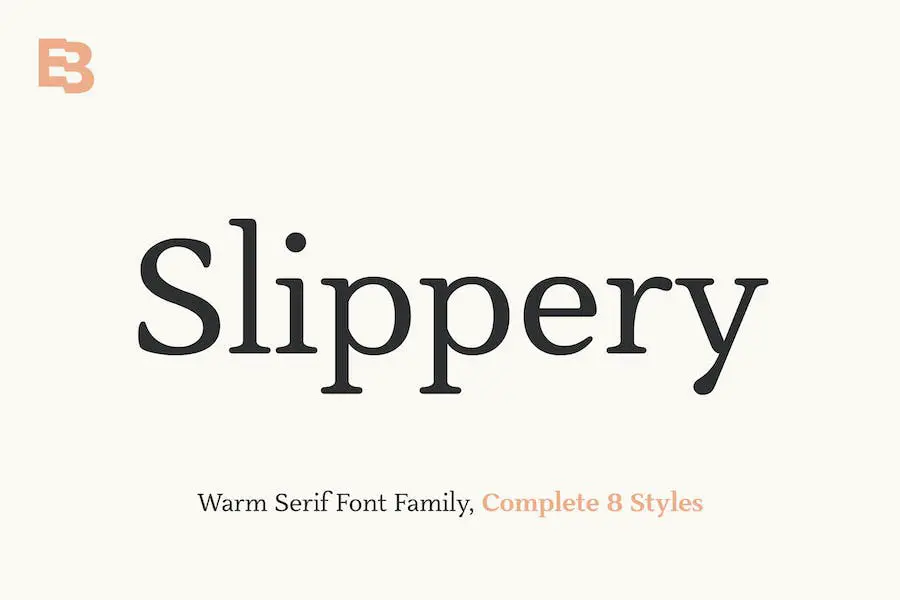
Slippery는 가독성을 높이기 위해 특별히 디자인된 따뜻한 세리프 글꼴입니다. 서체는 부드러운 가장자리, 넓은 카운터, 적당한 x 높이 및 독특하고 우아한 느낌을 주는 아름다운 이탤릭체를 특징으로 합니다.
GT 리카르도
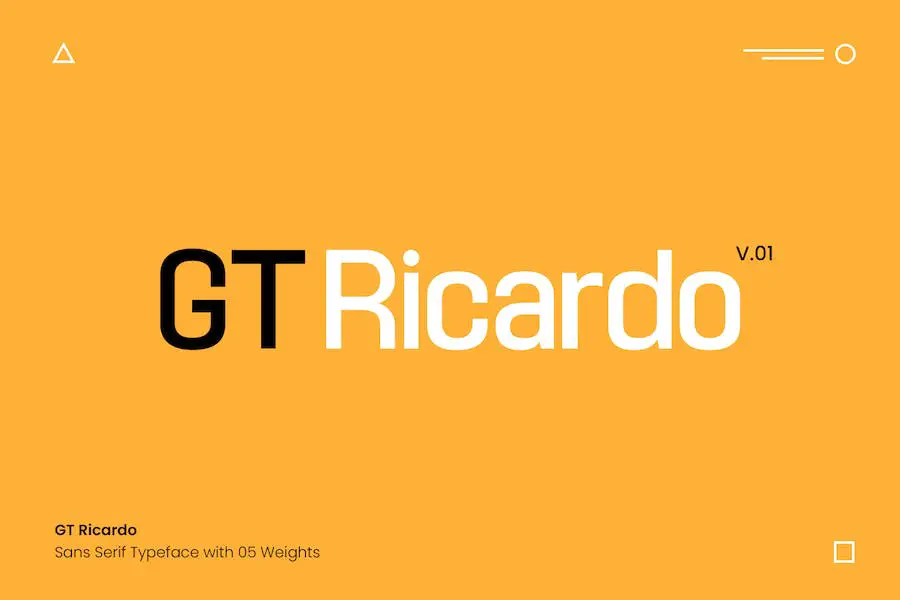
GT Ricardo는 Light, Regular, Medium, SemiBold, Bold 서체의 5가지 두께를 지닌 새롭고 우아한 서체입니다. 200개 이상의 글리프가 포함된 숫자와 확장 구두점을 제공하여 모든 프로젝트에 대한 다양성을 보장합니다.
전문적인 커닝과 품질 높은 장인정신으로 인해 이 서체는 신뢰할 수 있는 선택이 되었습니다. 로고, 잡지, 영화 또는 기타 디자인 프로젝트 작업을 하든 GT Ricardo는 통제된 글자체와 현대적인 터치로 작업의 수준을 높여줄 것입니다.
깨끗하고 미니멀한 스타일은 가독성과 다양성을 유지하면서 따뜻함과 기발함을 발산합니다. 브랜딩부터 헤드라인, 캡션, 문단, 포스터까지 GT Ricardo는 아름다움을 타협하지 않고 지속적인 인상을 남길 수 있도록 디자인되었습니다.
벨리아우
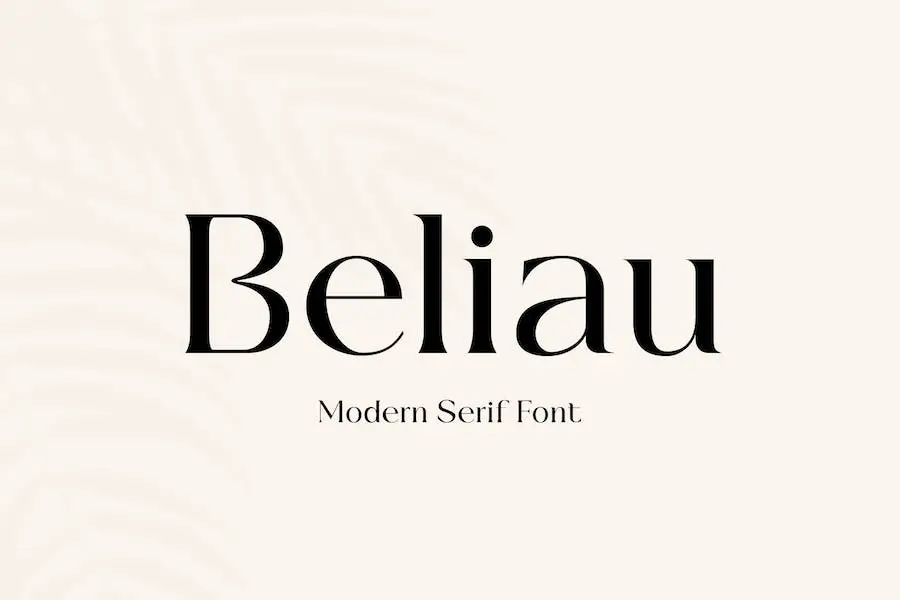
Beliau는 고해상도 디스플레이 및 인쇄 매체용으로 특별히 제작된 놀랍고 현대적인 세리프 글꼴입니다. 우아한 미학과 균형 잡힌 비율 덕분에 헤드라인, 기업 브랜딩 및 세련미가 필요한 기타 디자인 프로젝트에 사용하기에 이상적입니다.
최신 기술을 염두에 두고 설계된 Beliau는 심지어 가장 발전된 화면에서도 모든 캐릭터가 선명하고 명확하도록 보장합니다. 부드러운 선과 정밀한 디테일은 텍스트에 세련미를 더해 시각적으로 매력적이고 읽기 쉽습니다.
웹사이트를 제작하든, 로고를 디자인하든, 인쇄 레이아웃 작업을 하든 Beliau의 다재다능함은 빛을 발합니다. 다양한 디자인 응용 프로그램에 쉽게 적응하여 프로젝트에 전문적이고 세련된 모습을 선사합니다.
메리북
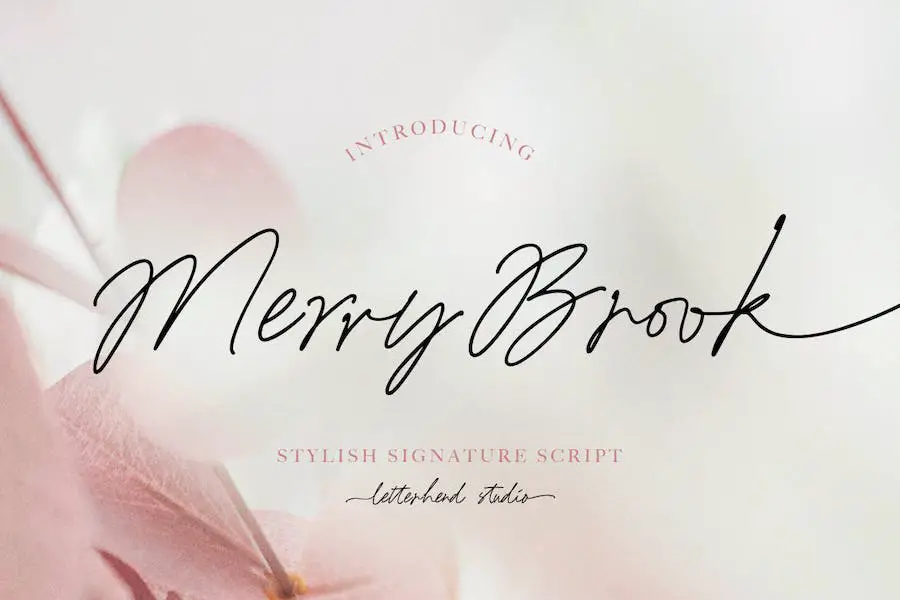
Merry Book은 손글씨의 유동성을 그대로 재현한 멋진 시그니처 스크립트 글꼴입니다. 스타일리쉬한 대체, 합자 및 섬세한 획을 갖춘 이 글꼴은 전통적인 타이핑 글꼴과 달리 실제 손으로 쓴 느낌을 만들어냅니다.
Merry Book은 로고, 초대장 및 라벨과 같은 공식 디자인, 잡지 레이아웃, 책, 인사말 카드, 포장, 패션 관련 프로젝트, 문구류, 소설 및 모든 광고 자료에 이상적인 선택입니다.
스타일리시한 대체 요소와 합자의 조합을 통해 다양한 범위의 디자인 가능성이 가능해졌습니다. 이 글꼴은 프로젝트에 개인적인 느낌을 더해 독특하고 손으로 만든 미학을 선사합니다.
콘테사
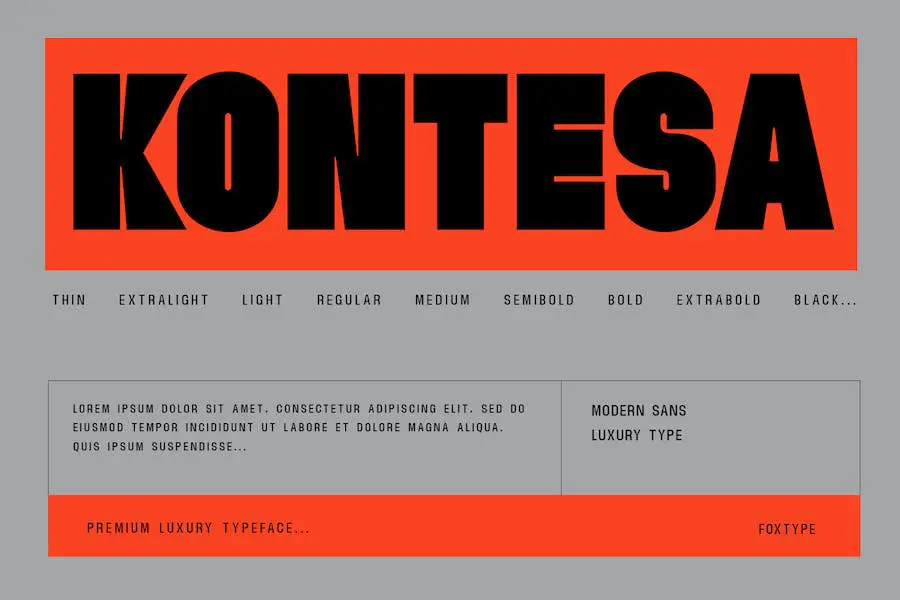
Kontesa는 모든 디자인 프로젝트에 신선하고 현대적인 느낌을 더해주는 우아하고 강력한 서체입니다. 신뢰할 수 있는 스타일과 제어된 문자 형식을 통해 멋진 로고, 시선을 사로잡는 잡지, 시선을 사로잡는 영화를 만드는 데 적합합니다.
이 글꼴은 브랜딩, 헤드라인, 캡션, 단락 및 포스터에 적합하며 디자이너가 다양한 응용 프로그램을 실험할 수 있도록 해줍니다. Kontesa의 다양한 무게는 다용성을 보장하므로 모든 창의적인 노력에 이상적인 선택입니다.
깨끗하고 미니멀한 미학은 가독성을 유지하면서 따뜻함과 기발함을 발산합니다. 인상을 남기고 싶거나 단순히 디자인의 아름다움을 향상시키려는 경우 Kontesa는 귀하의 기대를 뛰어넘는 글꼴입니다.
책벌레
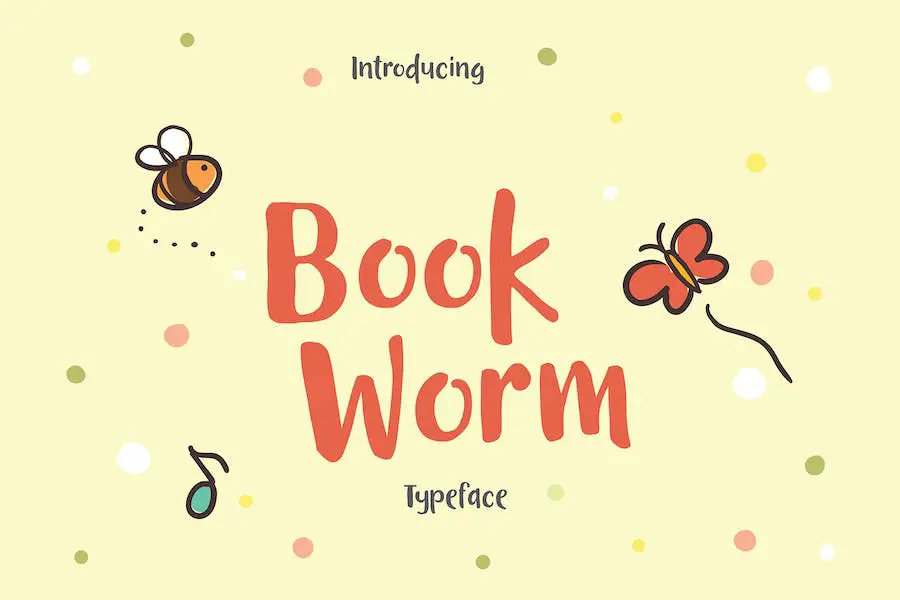
Book Worm은 디자인 프로젝트에 사용할 때 순수한 즐거움을 선사하는 글꼴입니다. 재미있고 기발한 품질을 갖고 있어 어린이다운 디자인, 특히 생일 초대장을 만드는 데 적합합니다.
이 유쾌한 서체는 붓으로 쓴 손글씨에서 영감을 얻었으며 동화책에 나오는 매력적인 그림을 연상시킵니다. 읽기 쉽고 재미있는 캐릭터로 모든 독서 경험에 재미를 더해줍니다.
Book Worm에는 간단한 합자, 숫자, 구두점이 포함되어 있어 인용문, 제목, 심지어 본문에도 사용할 수 있습니다. 그러니 창의력을 마음껏 발휘해 보세요. Book Worm으로 어떤 걸작을 만들어낼지 무척 기대됩니다!
이야기 시간
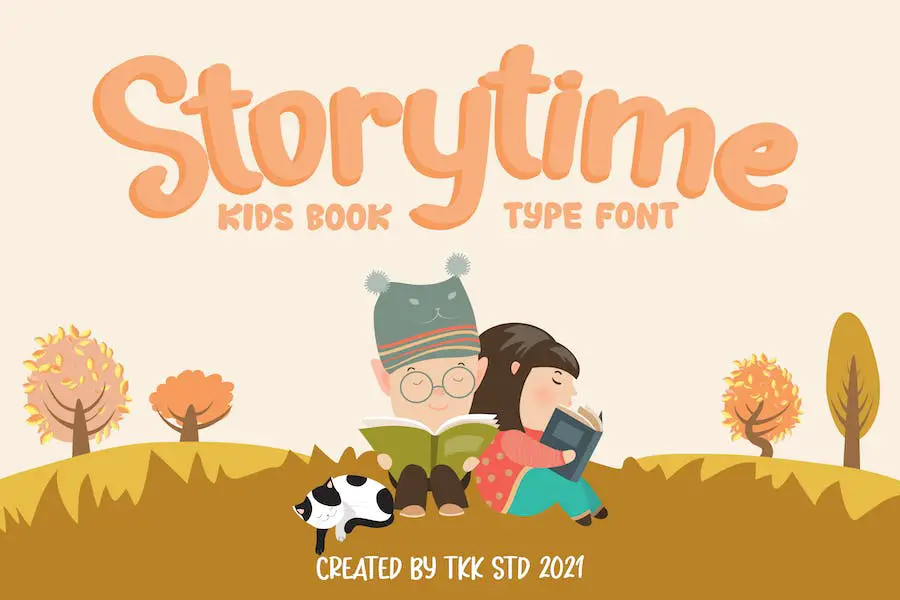
Storytime은 어린이 손글씨의 본질을 프로젝트에 적용하는 글꼴입니다. 이를 사용하면 즉시 따뜻하고 친숙한 분위기가 조성되어 독자, 특히 어린이가 집에 있는 듯한 느낌을 받게 됩니다.
가독성을 세심하게 고려하여 디자인한 글꼴은 아이들이 이야기에 계속 몰입할 수 있도록 해줍니다.
이 글꼴은 다양한 응용 프로그램에 완벽한 선택입니다. 낙서 글꼴 디자인을 만들고 식품 포장 글쓰기에 재미있고 창의적인 느낌을 더하는 데 적합합니다. 카페테리아 벽에 글을 쓰기에도 적합하여 공간에 활기차고 어린이 친화적인 분위기를 선사합니다.
페리카노
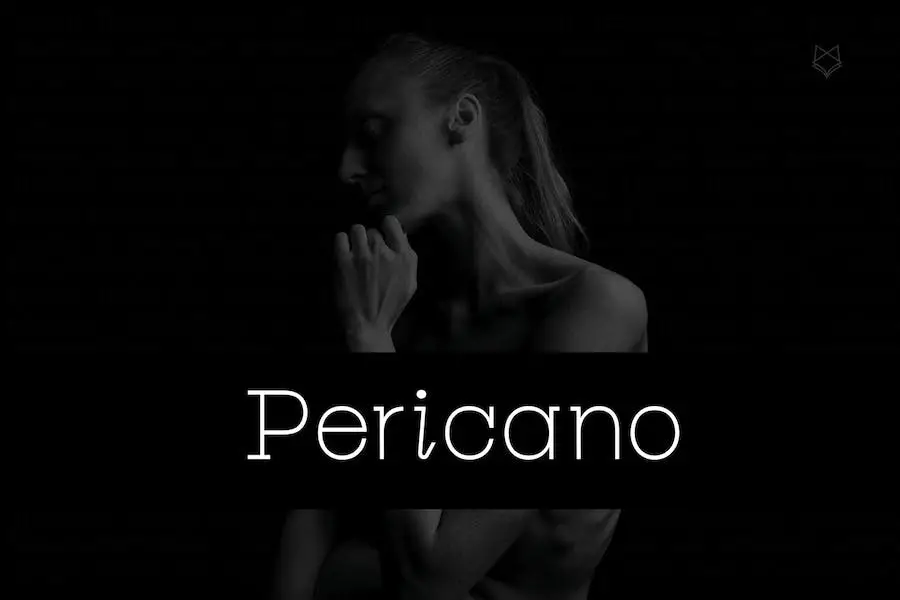
Pericano는 'It Display'라는 새로운 우아한 슬랩 세리프 서체입니다. 이 강력한 글꼴 모음은 제어된 문자 형식과 현대적인 터치를 결합하여 신뢰할 수 있고 타협하지 않는 스타일을 제공합니다.
로고, 잡지, 영화 등 어떤 용도로든 페리카노는 정말 멋져 보입니다. 브랜딩, 헤드라인, 캡션, 단락 및 포스터를 위한 완벽한 선택입니다.
다양한 가중치를 통해 프로젝트에 딱 맞는 애플리케이션을 자유롭게 실험하고 찾을 수 있습니다. 페리카노의 가장 좋은 점 중 하나는 아름다움과 가독성을 희생하지 않고도 강한 인상을 준다는 것입니다.
스모 북
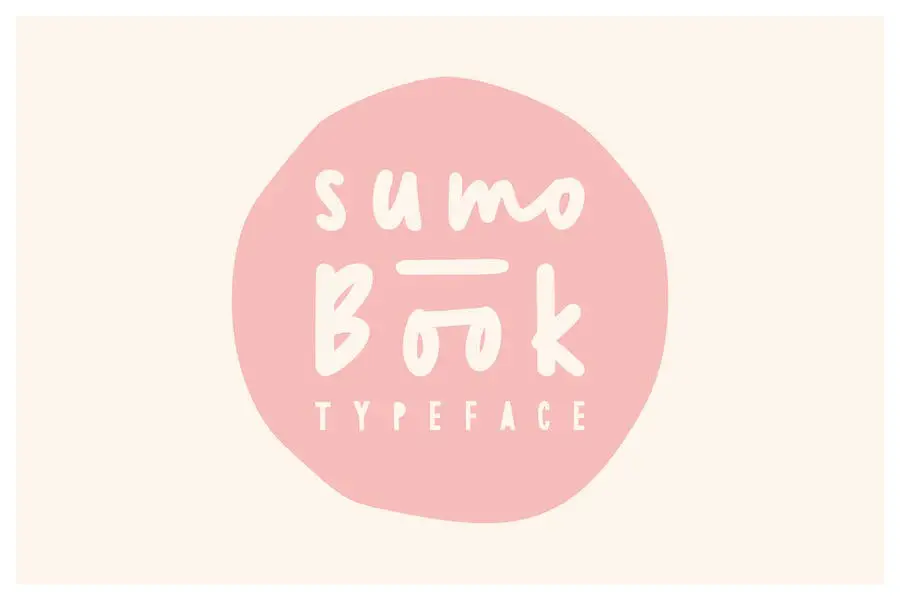
Sumo Book은 일반, 대문자, 대체, 대문자 대체는 물론 웹 글꼴 버전을 포함한 다양한 변형으로 제공되는 다용도 글꼴입니다.
합자도 포함되어 있지만 지원되는 프로그램에서 합자에 액세스하는 방법에 대한 자세한 내용은 제공된 링크를 확인하세요.
청키
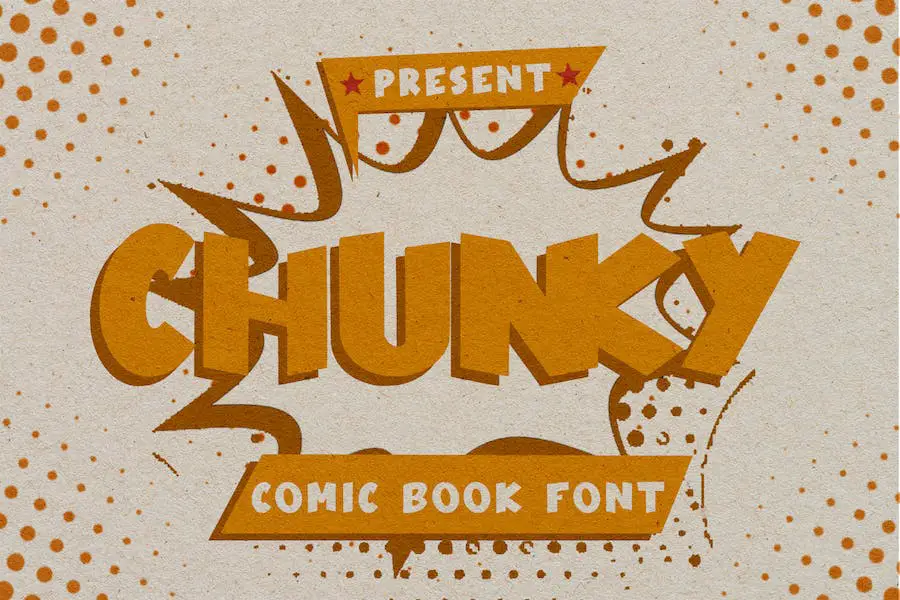
Chunky는 'It – Comic Book Font'라는 다목적 글꼴입니다. 소문자와 대문자, 기호가 모두 포함되어 있으며 여러 언어를 지원합니다. 이 글꼴은 추가된 디자인 옵션을 위한 다양한 합자를 제공합니다.
또한 문체 대체 및 기타 특수 기능도 포함되어 있습니다. Chunky는 패션 디자인, 브랜딩, 카탈로그 등과 같은 다양한 디자인 프로젝트에 적합합니다.
농담어린이
KiddingChildren은 아동 도서, 표지 또는 학교 행사에 적합한 다용도 글꼴입니다. 어떤 디자인에도 재미있고 캐주얼한 느낌을 더해 주면서도 깔끔하고 깨끗한 룩을 유지합니다.
스퀴시 블루
Squishy Blue는 어린이 테마북, 경제 포스터, 문구류, 학용품 폰트, 유튜브 커버, 유튜브 썸네일, 소셜 미디어 페이지 커버 등 다양한 프로젝트에 딱 맞는 글꼴입니다.
만화적인 느낌을 갖고 있으며 모든 문장에 대해 뛰어난 가독성을 제공합니다. 둥근 모서리와 베이스라인의 약간의 불규칙성은 친근감을 더해 아이들에게 더욱 매력적으로 다가옵니다.
일기장
Diary Book은 우아함과 매력을 발산하는 아름답게 제작된 손글씨 글꼴입니다. 다양한 대체 문자와 합자를 갖춘 이 글꼴을 사용하면 다양한 스타일에 액세스하고 프로젝트에 완벽하게 어울리는 고유한 표시 글꼴을 만들 수 있습니다.
결론
결론적으로 우리는 북 디자인 프로젝트에 적합한 글꼴을 선택하는 것의 중요성에 대해 논의했습니다. 우리는 책의 전반적인 디자인과 가독성을 향상시킬 수 있는 다양한 책 글꼴을 탐색했습니다.
선택한 글꼴은 독자의 경험에 큰 영향을 미칠 수 있으므로 책의 톤과 장르에 맞는 글꼴을 선택하는 것이 중요합니다.